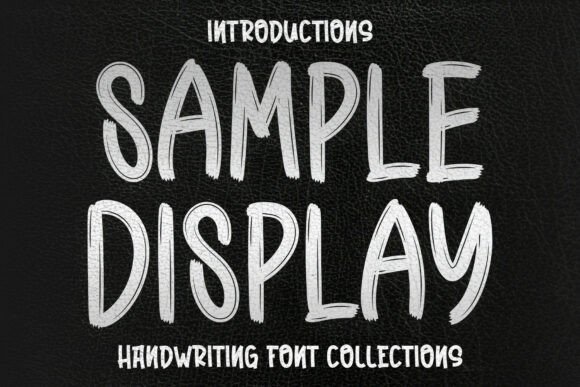
Sample Display
適切なデザイン要素を見つけるのは難しい場合がありますが、Sample Displayは作品を即座に引き立てる優れたコレクションを提供します。
POD(オンデマンド印刷)製品、結婚式の招待状、またはソーシャルメディアのグラフィックを作成している場合でも、Sample Displayは理想的です。